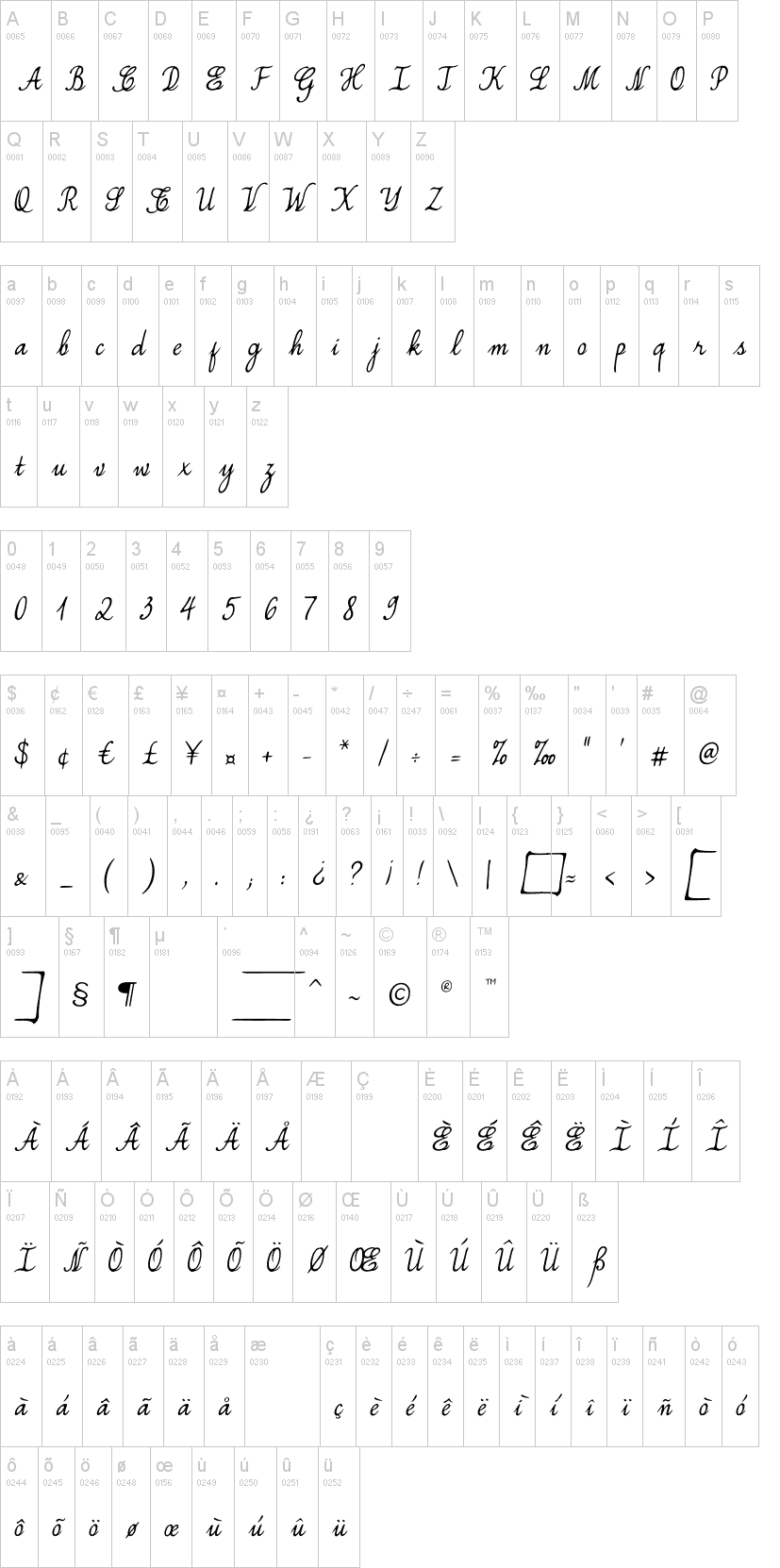
Simplesnails
? Simplesnails 字体是一款简洁、灵活的英文字体,由英国设计师 Simon Stratford 创作。它非常适合用于网页设计、图片处理和排版。Simplesnails 字体的特点是简洁大方,字体结构紧凑,易于阅读,易于排版,可以在大小屏幕上得到良好的显示效果。此外,它还具有良好的可读性,能够提供清晰的文字图像。
Simplesnails是一款非常不错的手写艺术字体,具有很好的视觉感,适合于文化类的宣传设计、商业类品牌的广告和产品包装设计以及个性化文字排版等较多场景。